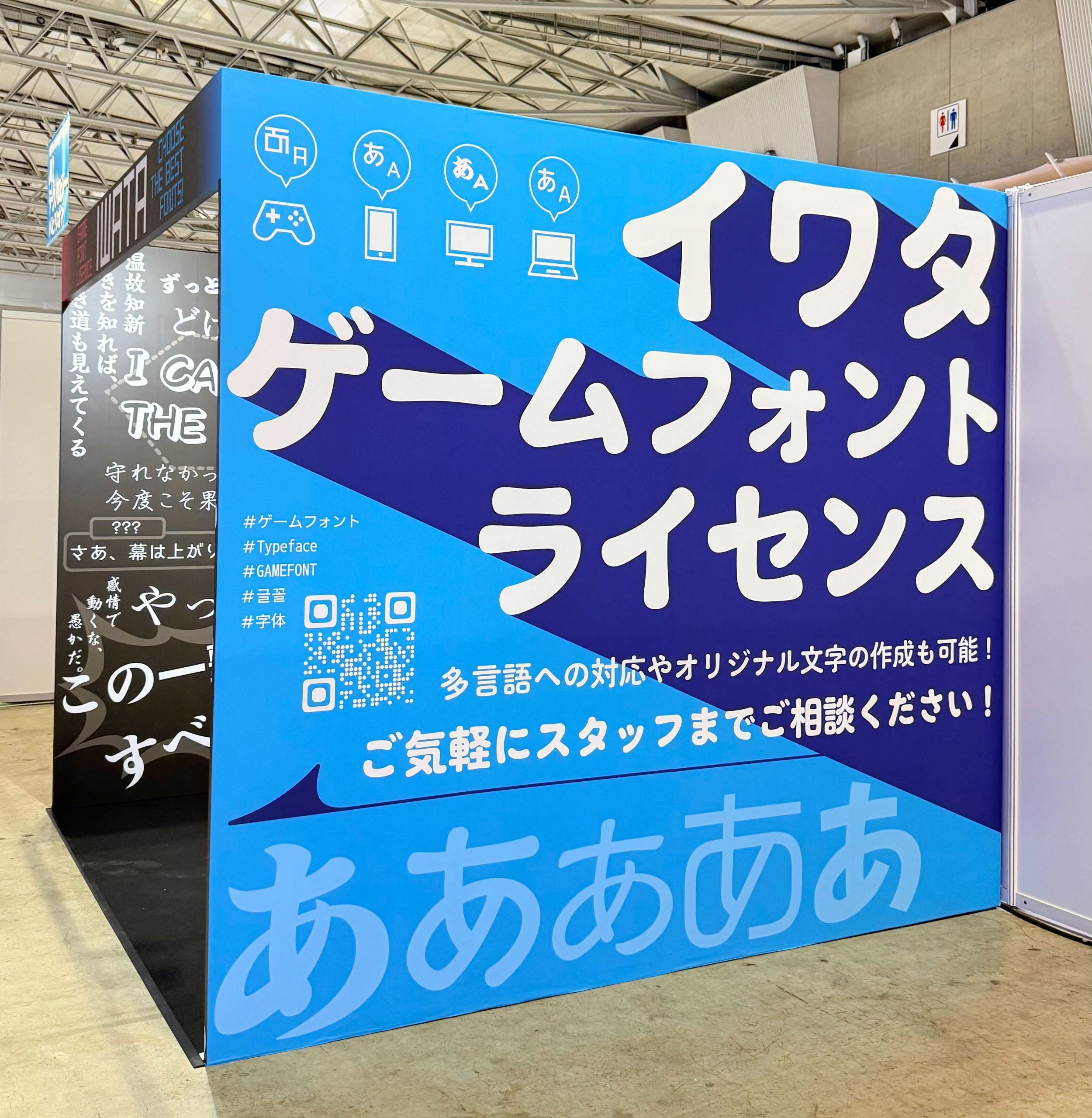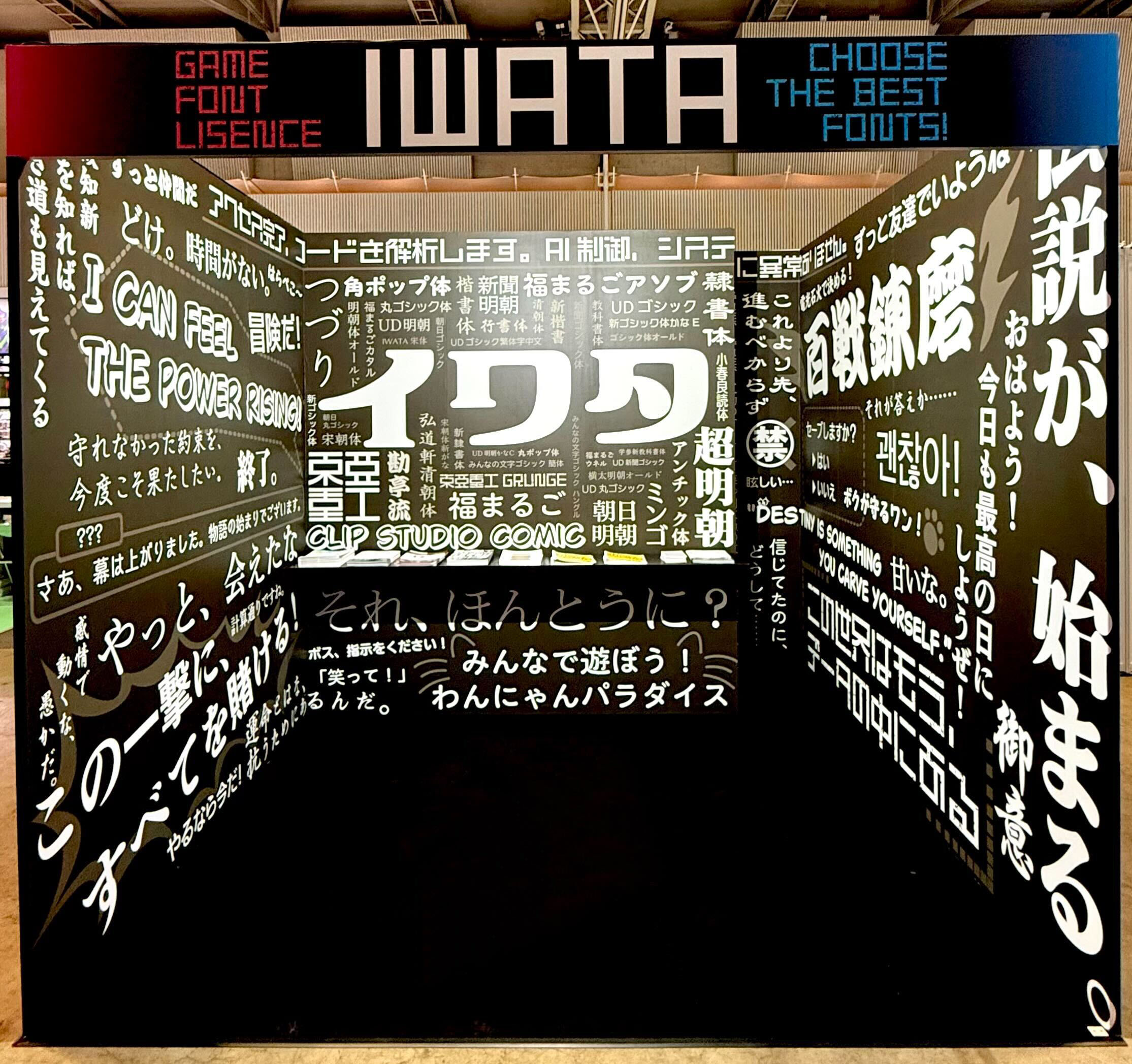
『東京ゲームショウ2025』に出展いたしました。
| 出展内容 | 見やすさに配慮した『イワタUDフォント』、漫画家の弐瓶勉氏とのコラボレーションフォント東亜重工製フォント『東亜重工』、さまざまなゲームタイトルで採用実績のある『イワタ新隷書体』などゲームの世界観に合わせたフォントをご紹介いたしました。 |
| 出展の みどころ | 日本最大級規模のコンピューターエンターテイメントの展示会『東京ゲームショウ』ビジネスデイに出展いたしました。 イワタのブースではゲーム内でフォントを表示する際に必要となる「ゲーム使用ライセンス」のご紹介とイワタ書体をまるごと楽しめるブース装飾が見どころです! |